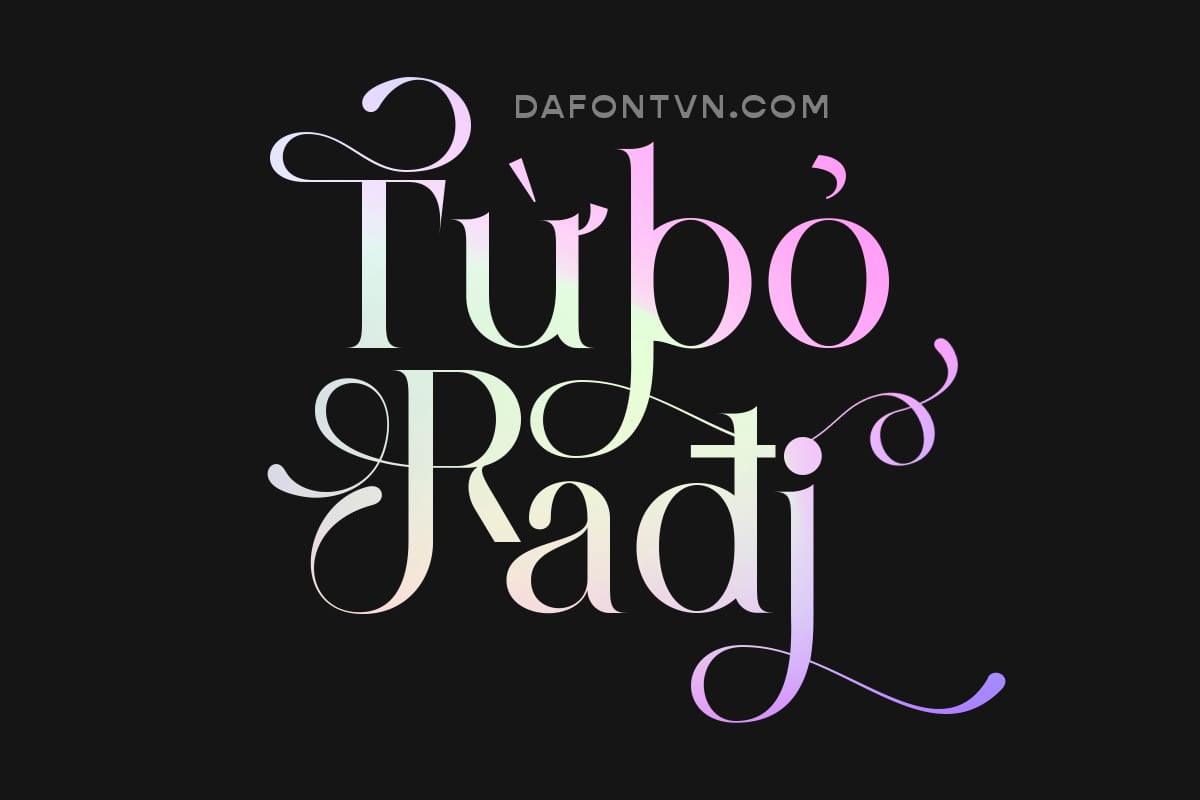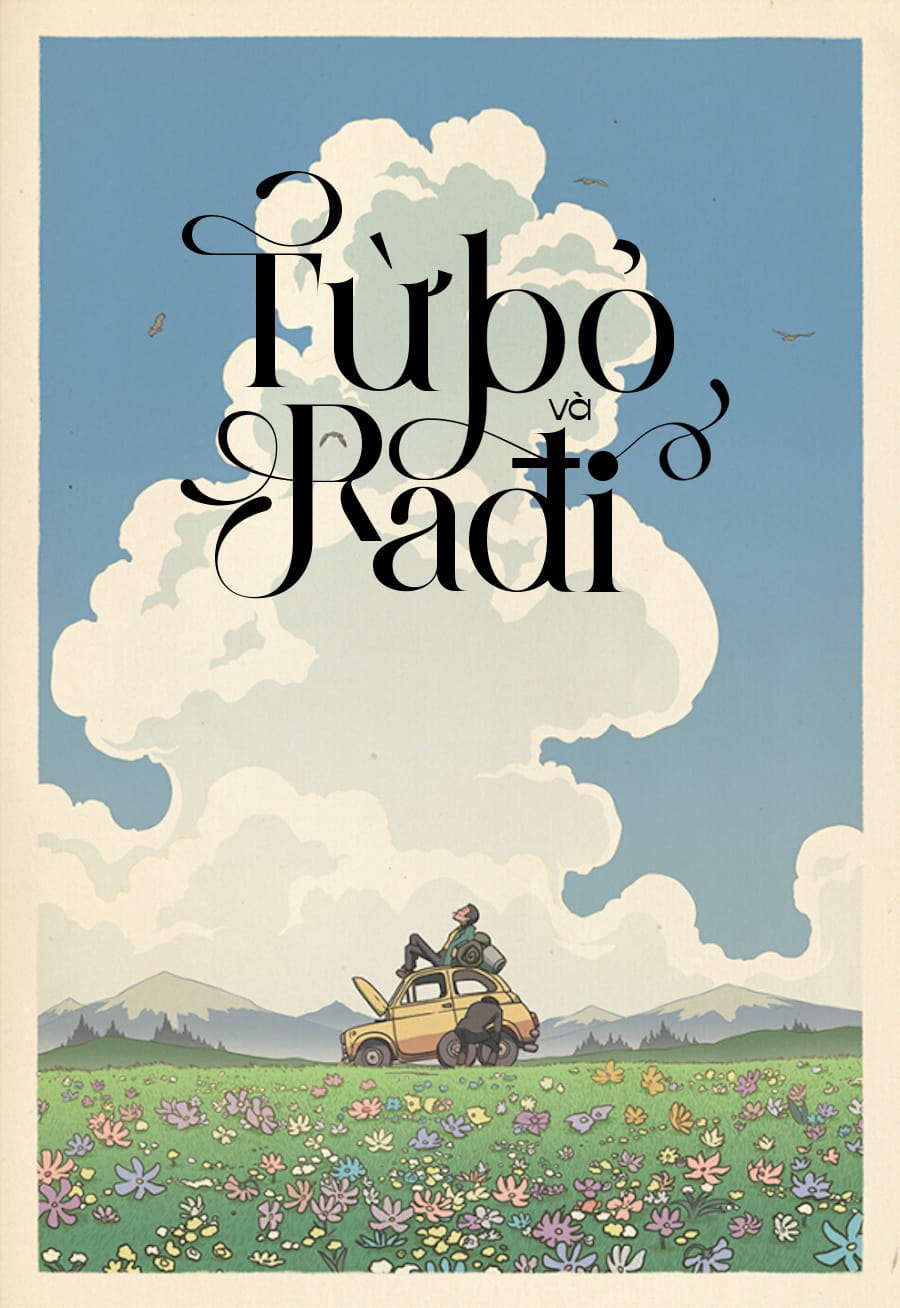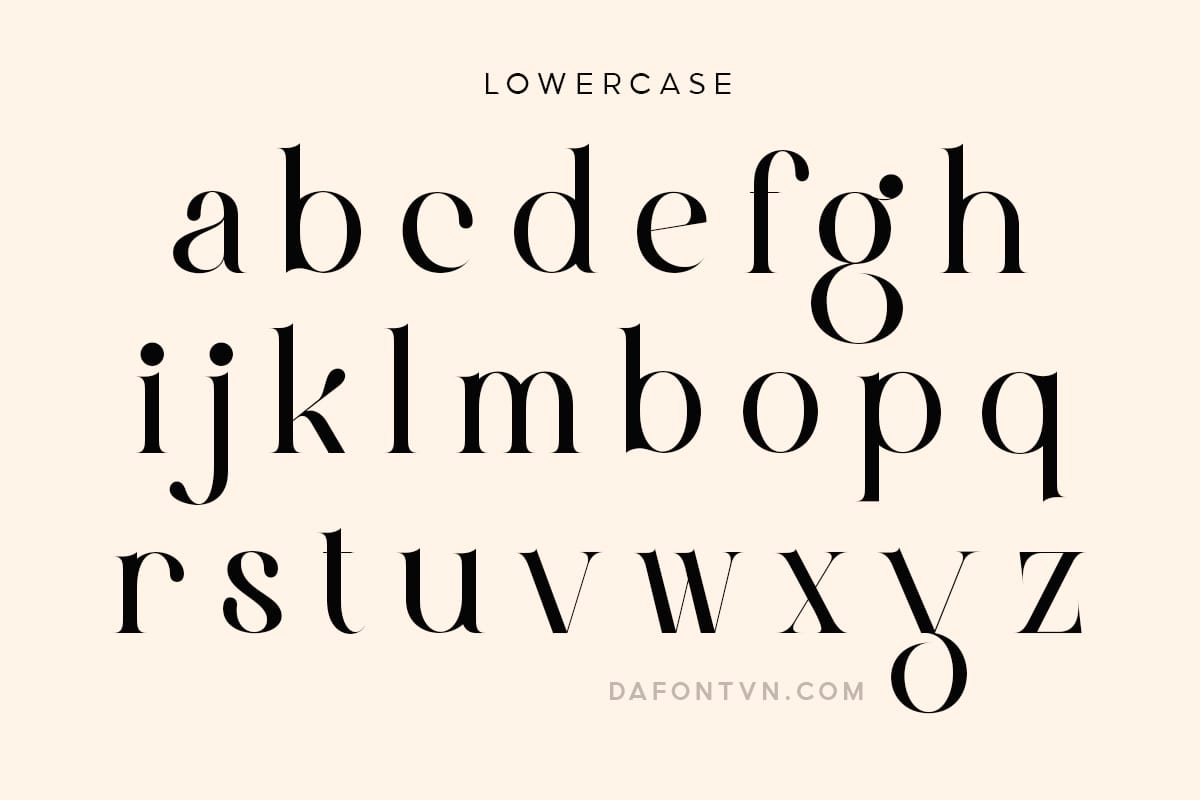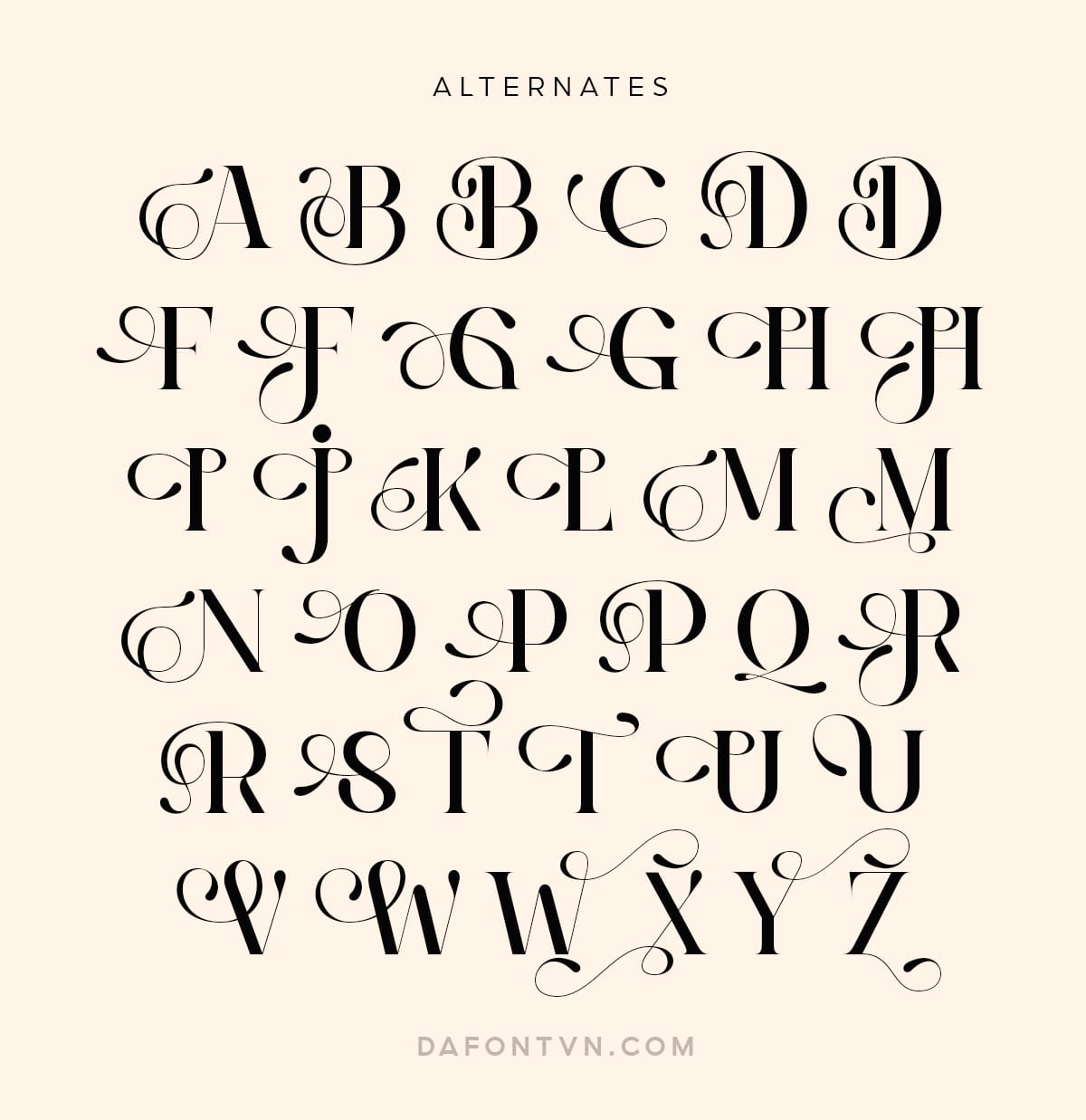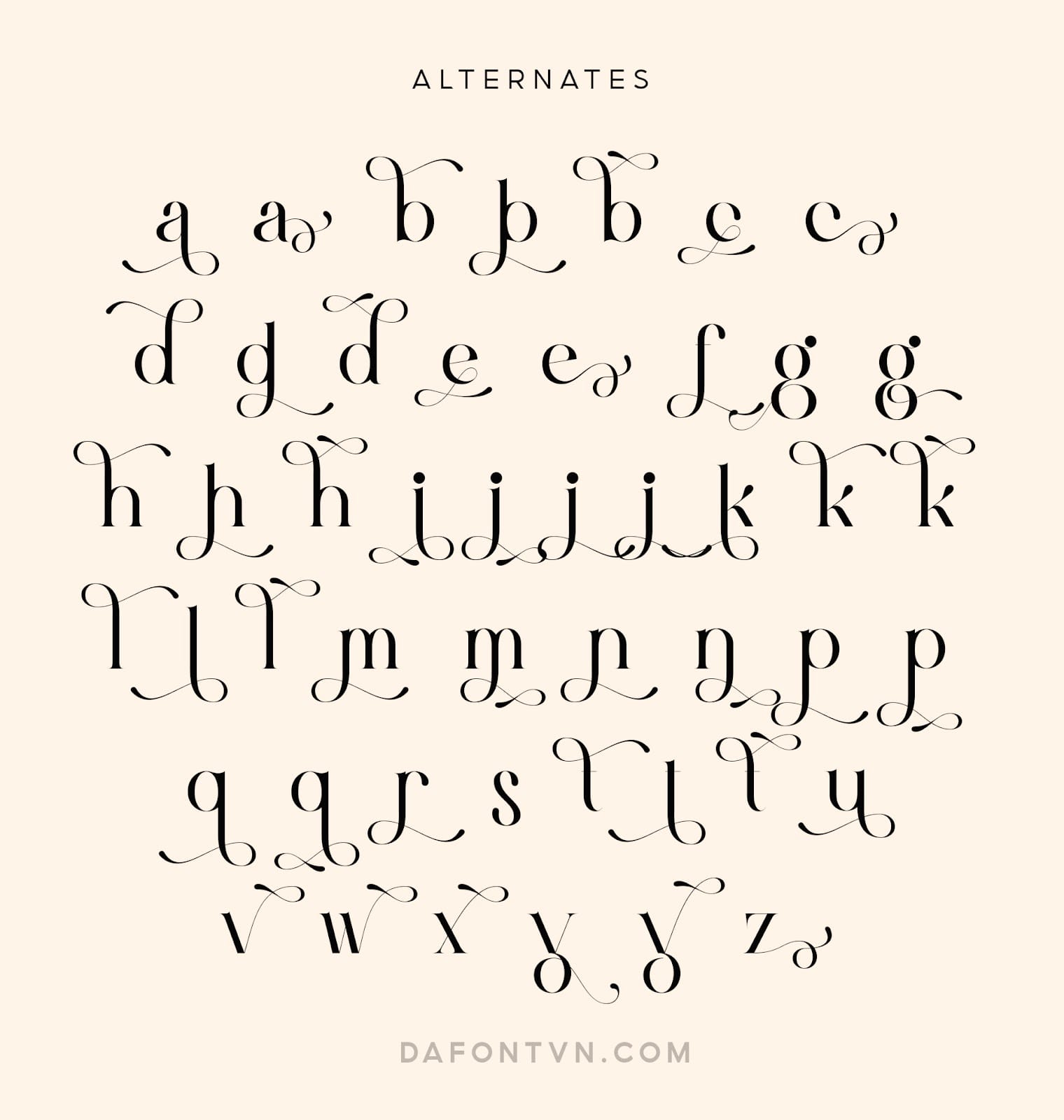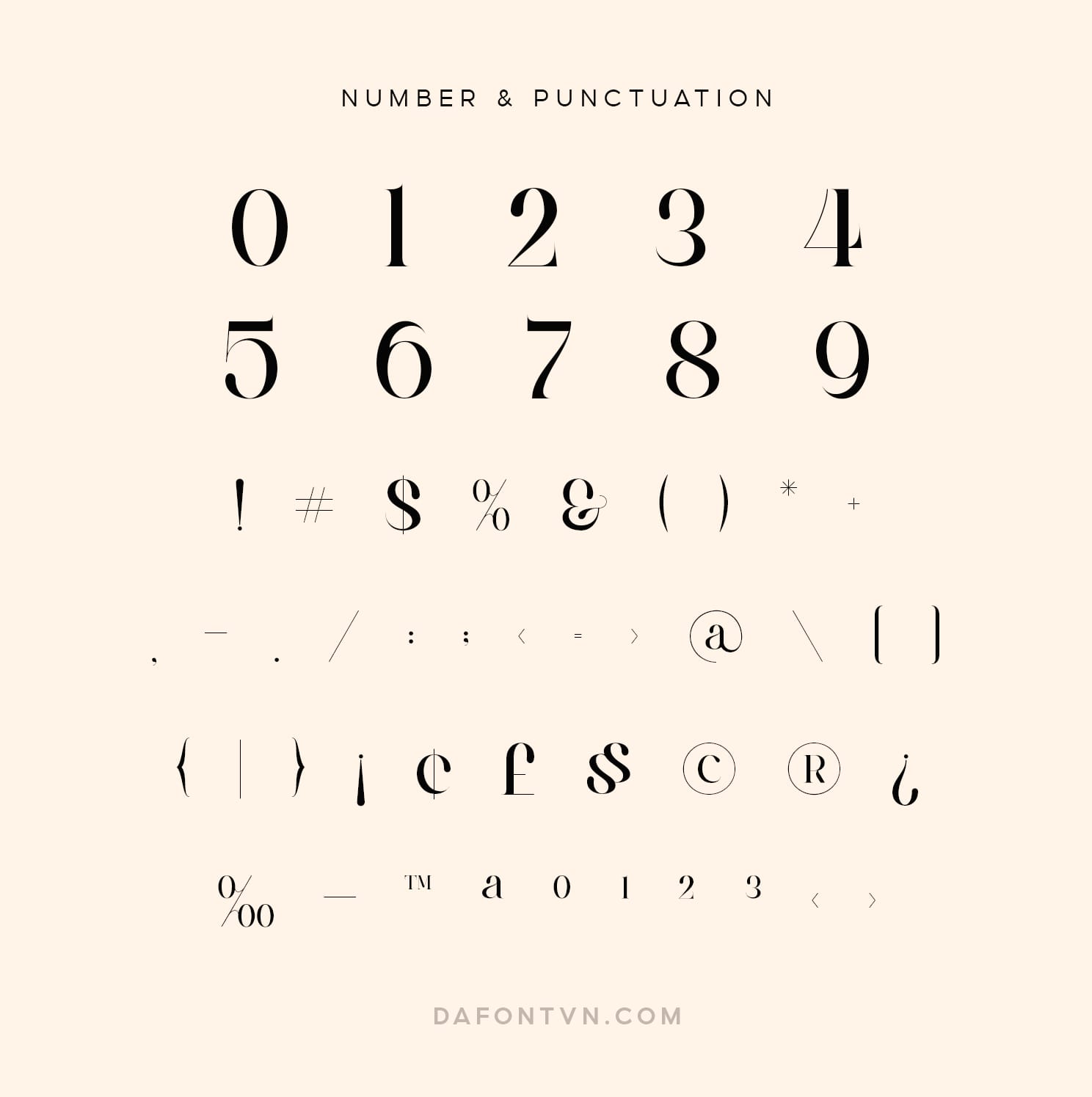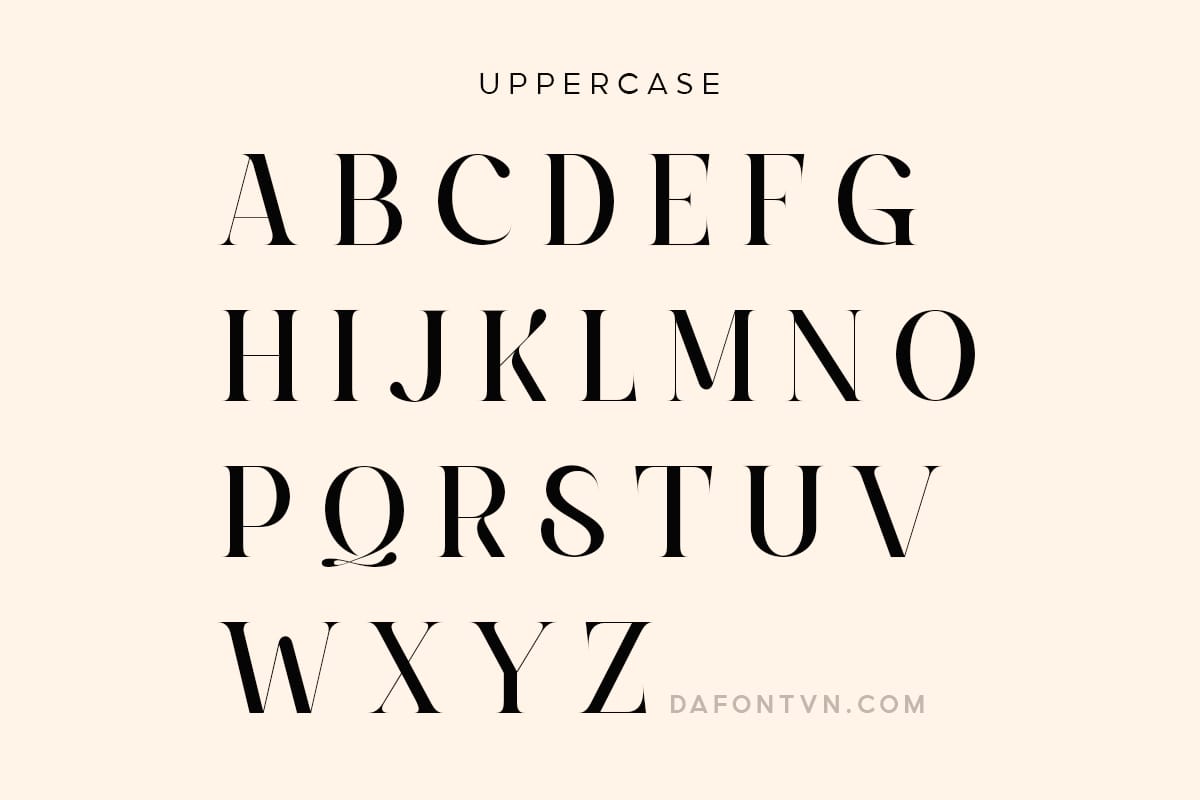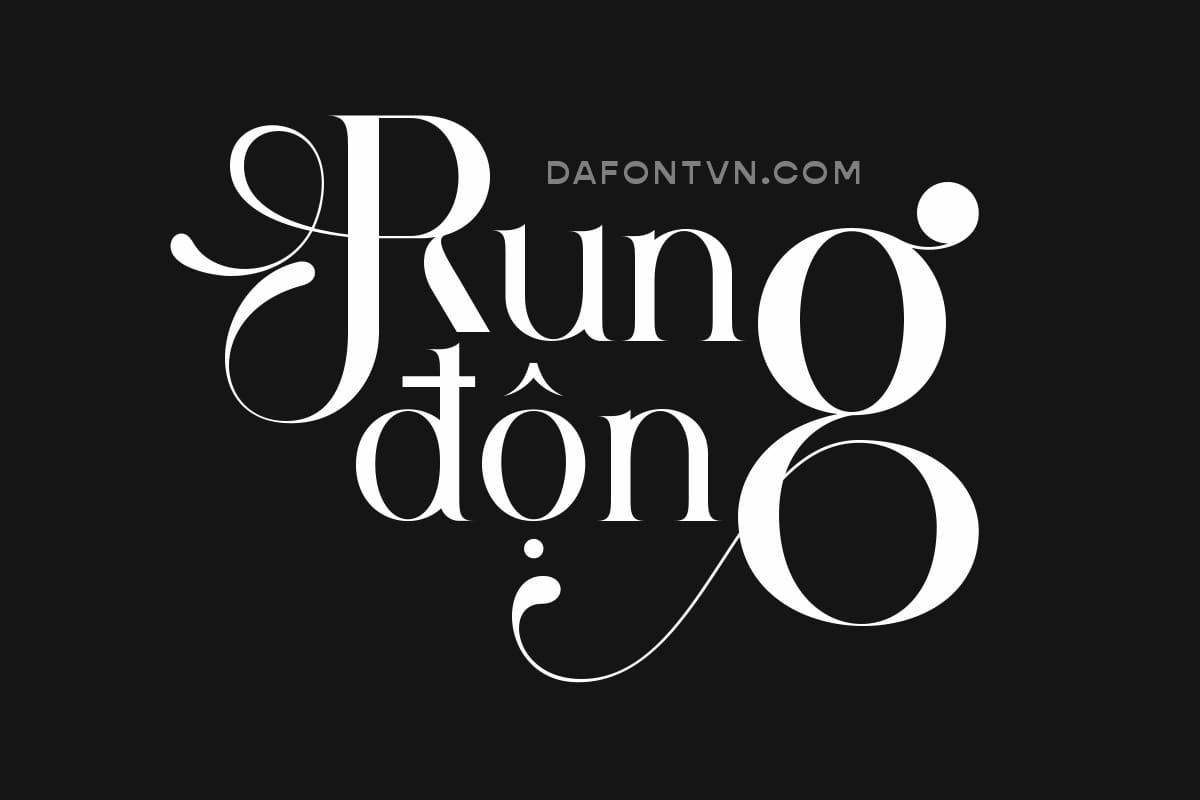
Kamerun Font là một kiểu serif được thiết kế đặc biệt cho nhu cầu xây dựng thương hiệu, có thêm chữ ghép và các chữ xen kẽ có hình dạng độc đáo để tăng thêm điểm nhấn cho các dự án thiết kế của bạn. Ngoài ra, bạn có thể sử dụng font Kamerun cho rất nhiều các thiết kế khác nhau như bìa sách, sản phẩm, tạp chí, quảng cáo, typography…
Font Kamerun Việt hóa đầy đủ, kerning lại và các dấu được vẽ lại hoàn toàn so với font gốc cũng như mã hóa PUA để sử dụng trên bất kỳ phần mềm thiết kế, phi thiết kế nào.